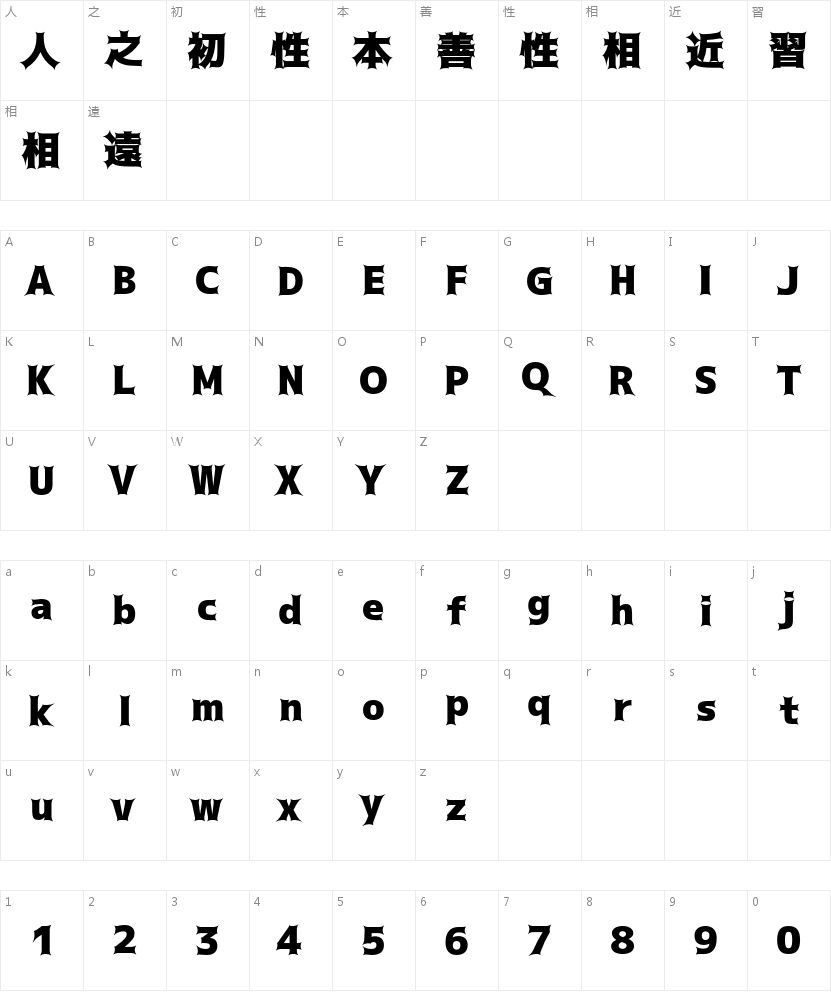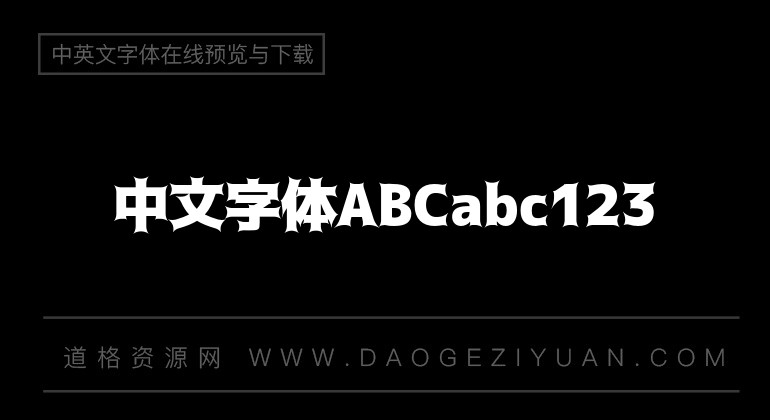
托加里特体(トガリテ)是一种日本汉字书法字体,具有独特的笔画风格。它是由日本著名书法家托加里龙仁(Togari Toru)所创造的。 托加里特体的字形独特,其笔画的粗细变化和笔画的起伏跳跃,使得这种字体的书写非常有趣,也非常具有装饰性。此外,托加里特体字体的笔画线条也非常有力和稳健,这使得它非常适合用于印刷和数字设计领域。 托加里特体的黑体(トガリテBlack)是托加里特体的一种变体。它保留了托加里特体的特色,但加重了笔画的宽度,使得字形看起来更加醒目和突出。托加里特体黑体常用于印刷、海报、广告设计等领域,适合需要突出重点和增强视觉效果的场合。文件名:Togalite-Black-2.otf
托加里特体トガリテ Black是一款非常不错的手写艺术字体,具有很好的视觉感,适合于文化类的宣传设计、商业类品牌的广告和产品包装设计以及个性化文字排版等较多场景。